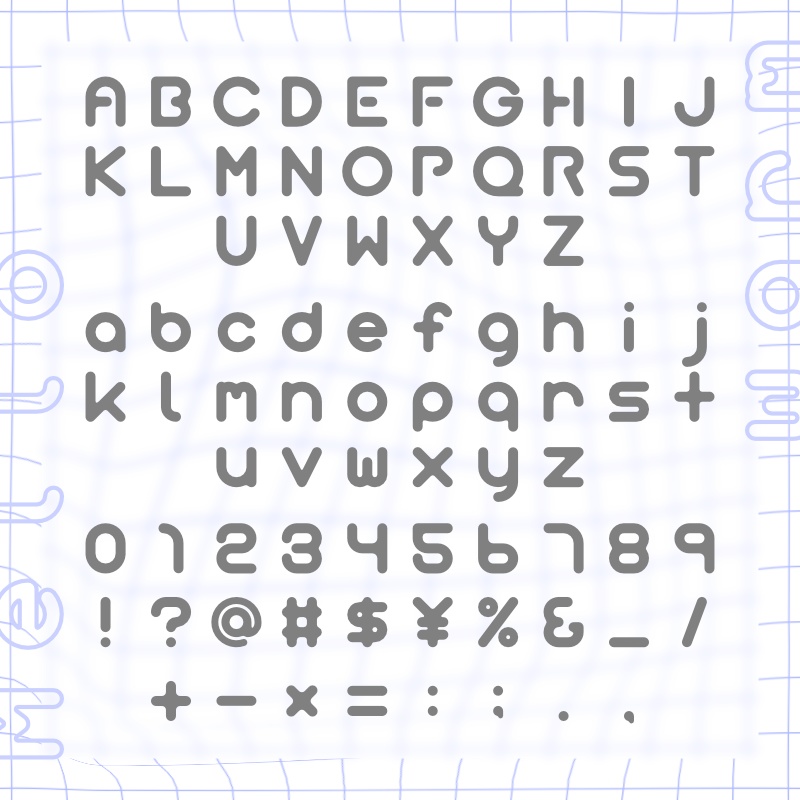
-Mellowarm- ・メロウォームと読みます、 ・まるく、まろやかでやさしいフォントです。 ・庶民用、富豪用、大富豪用、石油王用に違いはありません。製作者が喜ぶだけです。我こそは富豪なりという方は是非。 ------------------------------------- ○収録文字○ ABCDEFGHIJKLMNOPQRSTUVWXYZ abcdefghijklmnopqrstuvwxyz !?@#$¥%&_/+-×=:;,. 0123456789 ------------------------------------- ○使用について○ ・個人/商用利用を問わず、自由に無料で使用できます。(Twitterなどで教えてくれると嬉しい) ・同人誌等で使用した場合、奥付でここのURLを掲載していただければうれしいです。(しなくてもいいよ) ・改変や派生フォントの作成、ファイル、ソフトウェア、Webページへの組み込みも可能です。 ○注意事項○ ・全ての環境で正常に動作する保証はできかねます。また、当フォントを利用したことによって発生した故障、損害についても責任を負わないこととします。 ・派生・改変等の販売は禁止します。 ・再配布、製作者を名乗るのは禁止です。 ○zipファイル内容物○ Mellowarm-TrueTypeフォント readme_yondene-txtファイル(注意書き等) 製作者Twitter https://twitter.com/Zm_VCD